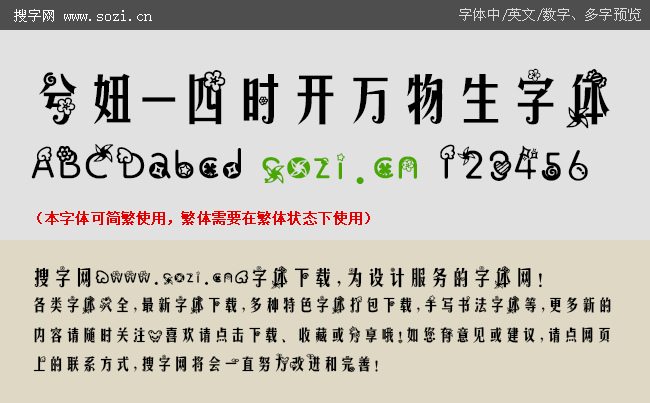
四時(shí)萬物生字體
搜字網(wǎng)給大家提供一款四時(shí)萬物生字體手機(jī)中文字體下載。這款手機(jī)字體是在迷你簡長藝體筆畫間插入了一些卡通化朵圖案。長藝體筆畫既有黑體的粗壯醒目,又有宋體的秀美柔和,加上藝術(shù)性的圓球形點(diǎn)、起筆如蝌蚪形的頓點(diǎn)、螺螄轉(zhuǎn)似的小鉤,配以修長的字形,如少女般婷婷玉立,裊娜動人,美觀而不落俗套。加入了卡通圖案后又增添了趣味性,特別適合喜歡手機(jī)字體個(gè)性一些的朋友在手機(jī)上安裝使用。